Web制作に役立てよう! フォントに関する便利なオンラインツールをまとめました。
Webサイトや印刷物などのデザインを作る上で「フォント」は欠かせません。
私はよく、電車の広告や街中の看板などに使われているフォントを観察しています。観察していると、世の中には数多くの種類のフォントが存在しているなと感動します。
デザインする上で、フォントの影響力は多大です。フォントの種類を変えるだけでデザインそのものの雰囲気が一気に変わってしまいます。
しかし、そんな数多くのフォントをうまく使いこなすのは大変ですよね。気付くと毎回同じフォントを使っていたり、いつかどこかで使えるだろうと思ってインストールしたフォントがあることを忘れてしまっていたり…。
今回はそんな悩みも解決できそうな、フォントに関する便利なオンラインツールをいくつかご紹介します。どれも無料・登録不要なのでぜひお試しください。
日本語のフリーフォントを探せる「ためしがき」
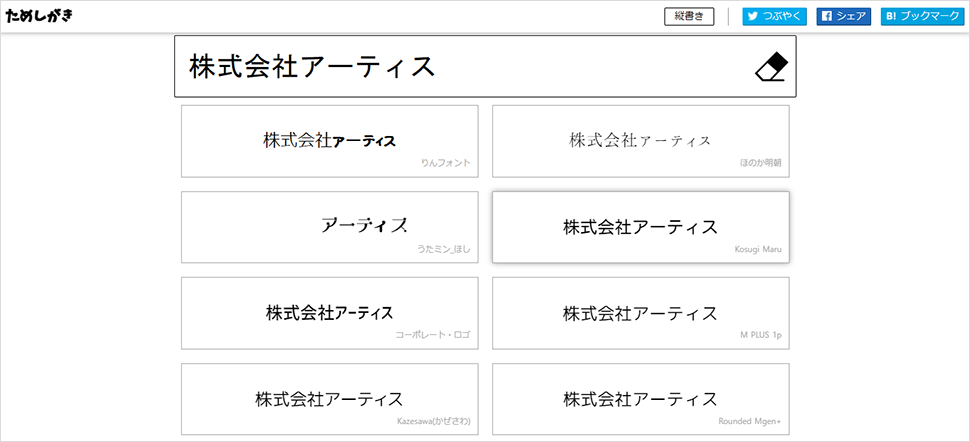
こちらは、日本語のフリーフォントを探せるサイトです。Googleフォントも含んでいます。
その名の通り検索窓に“ためしがき”すると、いろんなフォントでその単語が表示されます。使いたい漢字がそのフォントに対応しているのかも調べることができ、非常に便利です。
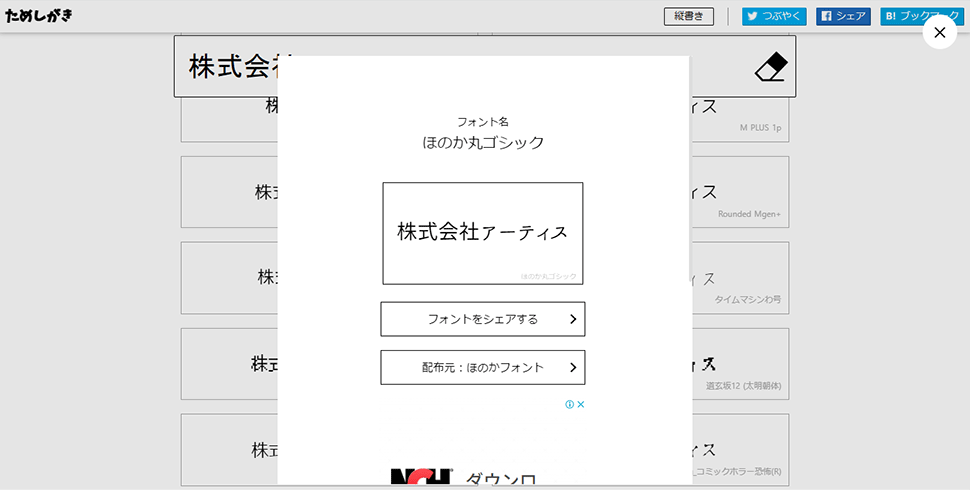
▲見た感じ、すこし癖のあるフォントが多い印象です。
英語のフリーフォントを探せる「font space」
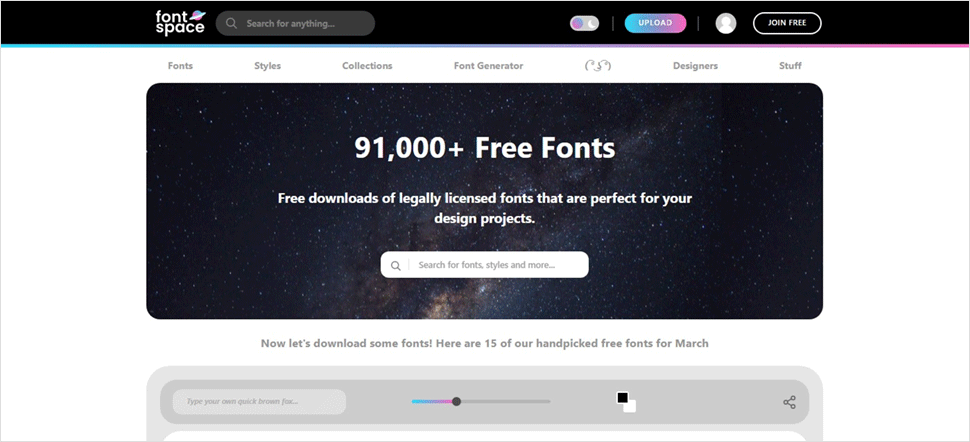
こちらは英語のフリーフォントを探せるサイトです。たくさんのフォントが登録されています。(2022年3月時点で91,000種類以上!)
[styles]では、カテゴライズされたフォントを形状から検索できます。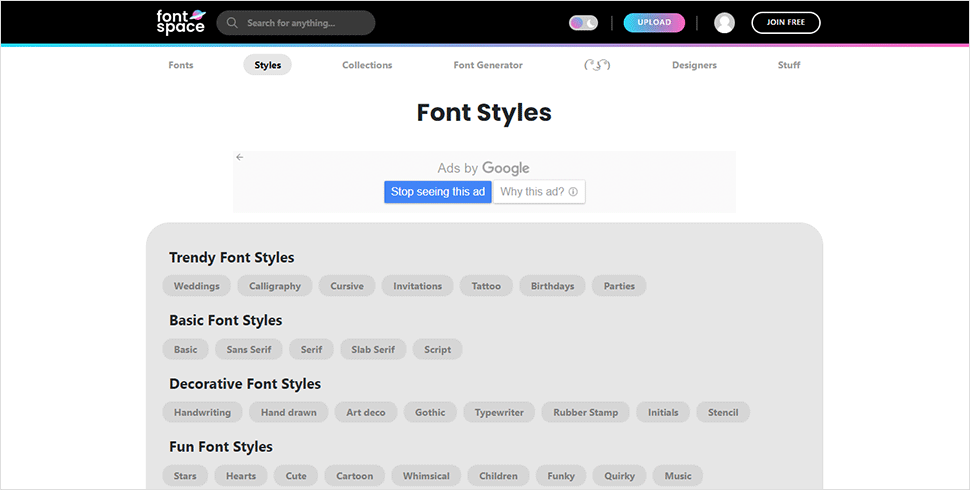
PCにインストールされているフォントをブラウザ上で一覧表示できる「wordmark.it」
フォントをダウンロードしすぎて、いま自分のPCにどんなフォントがインストールされているのかわからなくなってしまうときがありませんか?
IllustratorやPhotoshopのフォント選択エリアでも参照できますが、それよりももっと見やすくフォントを参照・比較できるツールがあります。
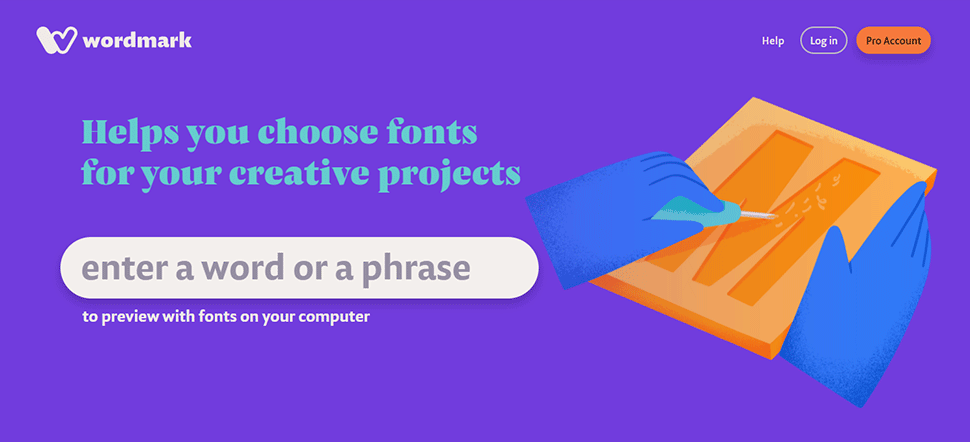
chromeに追加したら、探したいワードを入力します。
[Your Font]を選択すると、自分のPCにインストールされているフォントの一覧で、先述した「ためしがき」のようなことができます。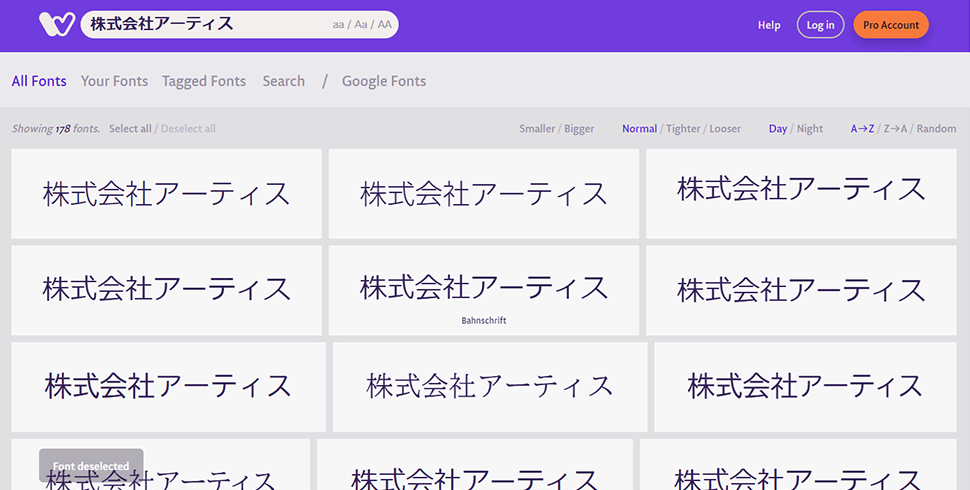
また、いくつかのフォントを選択し、右上にある「Filter selected」ボタンをクリックすると、選択したフォントのみを比べることもできます。
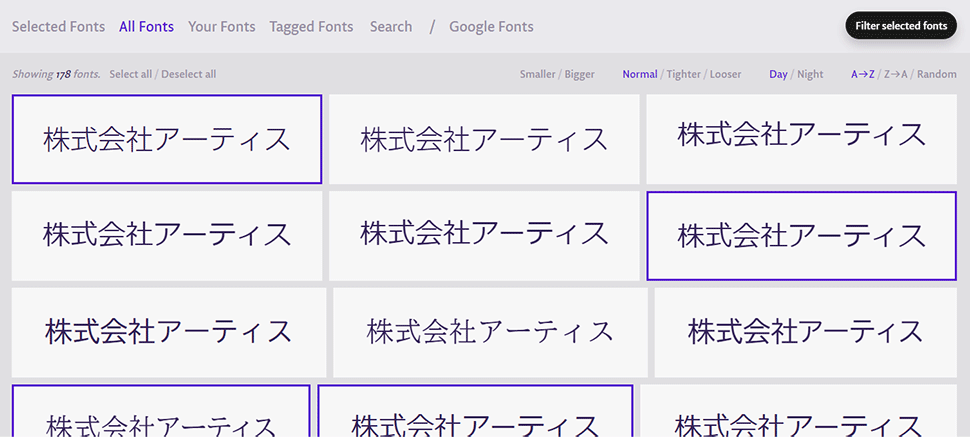
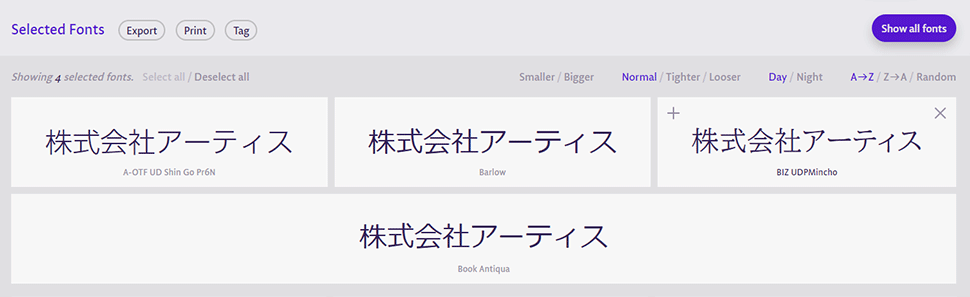
英語と日本語、両方に対応しています。
手持ちのフォントからイメージにあったフォントを探す時にとても便利ですね。
【おまけ】Adobe Fontでは、日本語フォントの一覧をダウンロードできます。
Adobe Fontのサイトでは、フォントの一覧を確認することもできますが、日本語書体の一覧をダウンロードすることができます。(2021年10月時点での資料)
ずらりと何かが並んでいる図鑑的なものが好きな人(私も含め)は、多分これは好きなのではないかと思います。
ダウンロードページに行ってみてわかりますが、Adobe Fontには日本語だけでもかなりの種類がありますね!
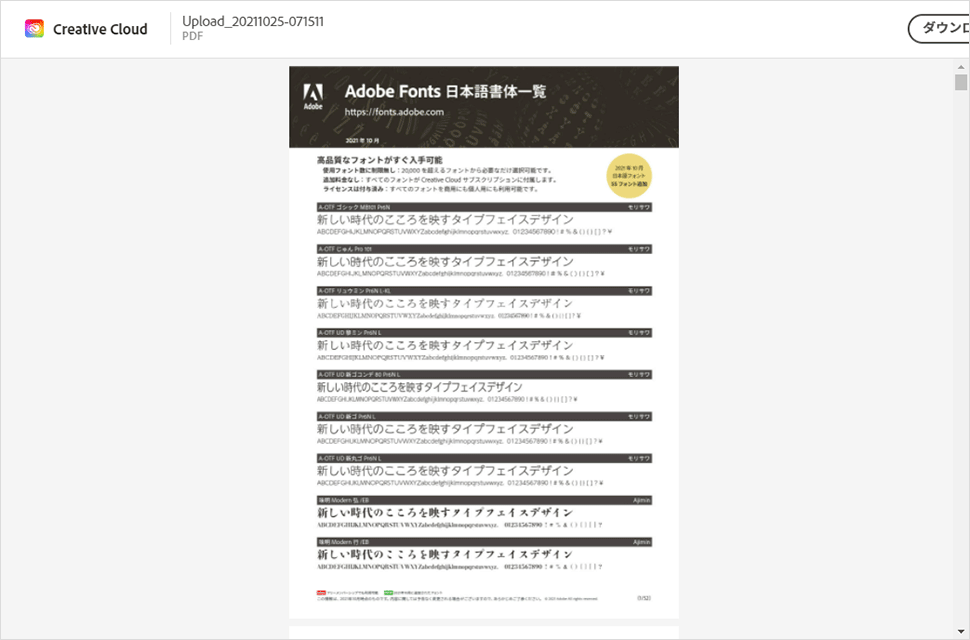
さいごに
数多くのフォントの中からイメージに合うフォントを探すのは大変です。
今回紹介したようなツールがあれば、フォント選びの手助けになり、Web制作での表現の幅が広がるかと思います。
個人的には、自分のPCに何のフォントをインストールしてあったのかをよく忘れてしまうので、「wordmark.it」はこれから活用していけそうだなと思いました。